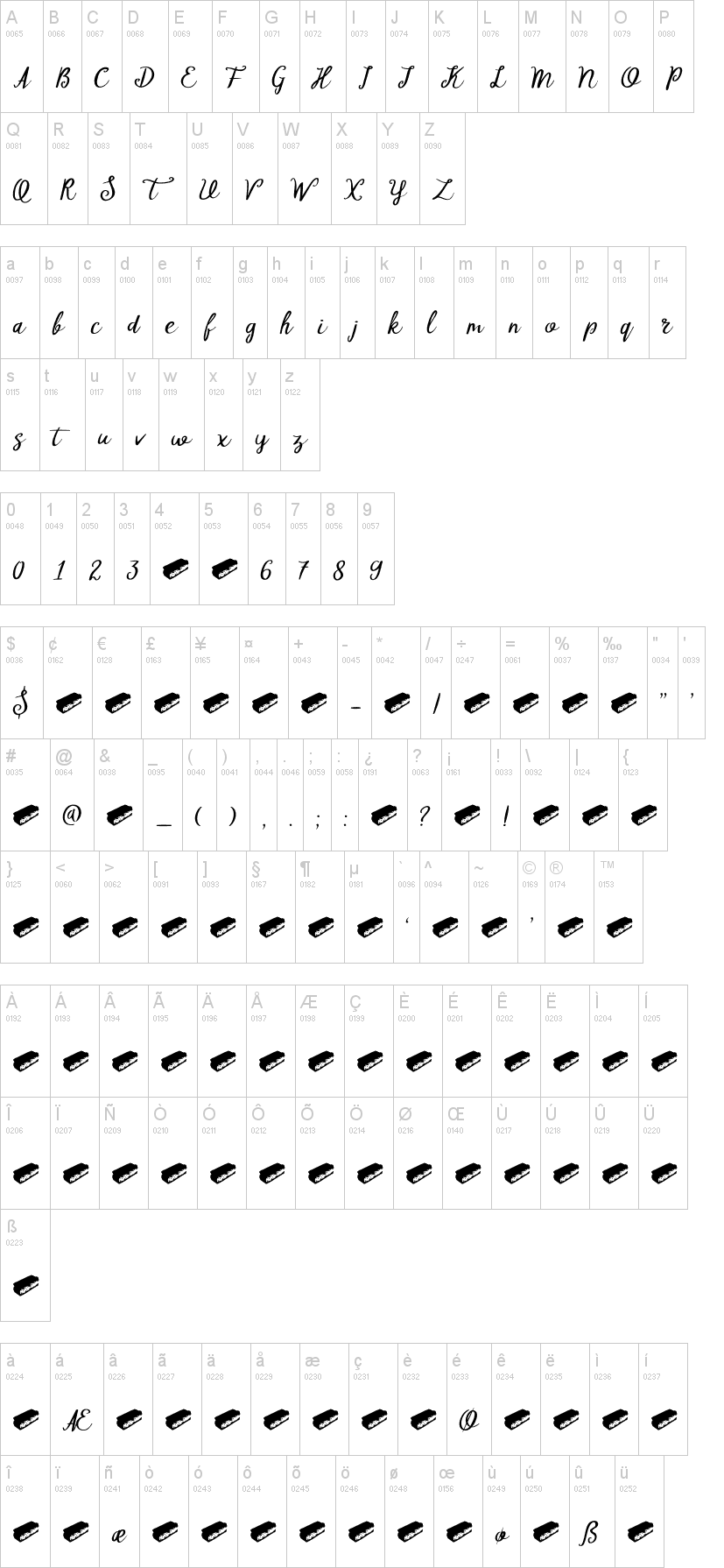
DK Tompouce
DK Tompouce 是一种手写风格的字体。它的风格非常华丽,有些像古老的信件或书籍上常见的字体。它的笔画比较有特点,看起来有点像手写笔刷的效果。此外,该字体的字母间距较大,呈现出一种轻松、自然的感觉。如果您需要制作一些有趣的海报、明信片或宣传单等文档,DK Tompouce 可能是一个不错的选择。
DK Tompouce是一款非常不错的手写艺术字体,具有很好的视觉感,适合于文化类的宣传设计、商业类品牌的广告和产品包装设计以及个性化文字排版等较多场景。